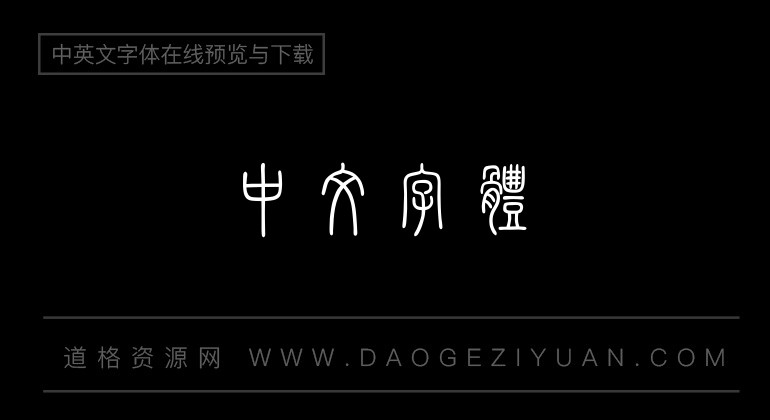
迷你繁篆书,又称“迷你篆书”,是一种以汉字为主要表现形式的书写字体。迷你繁篆书字体以繁篆字体的古老传统风格为蓝本,结合现代设计理念,精心调整繁篆字体的笔画粗细、笔画间距、笔画变化、笔画组合等,使字体更加精细、清晰、美观,且易于书写。迷你繁篆书字体的特点是:笔画细腻、结构规整、结构严谨、笔画细小、笔画间距小、笔画组合精细、笔画变化丰富、字体美观大方、书写舒适。文件名:MiNiFanZhuanShu-1.ttf
迷你繁篆书是一款非常不错的手写艺术字体,具有很好的视觉感,适合于文化类的宣传设计、商业类品牌的广告和产品包装设计以及个性化文字排版等较多场景。